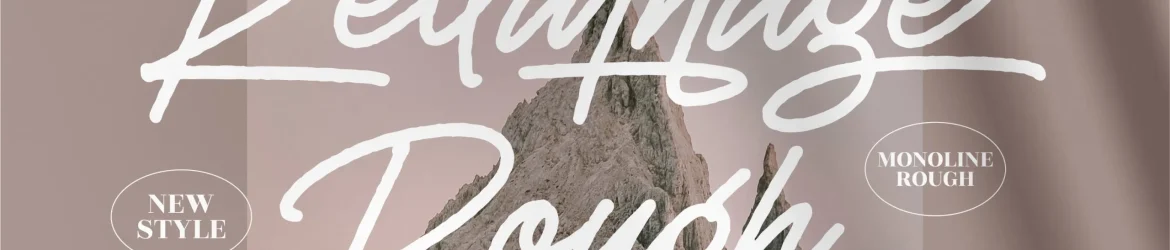
Rellathage Rough Font – Fonte Grátis
Rellathage Rough Font
A fonte “Rellathage Rough” é uma escolha ideal para projetos que exigem um toque autêntico e sofisticado. Com seu estilo handwritten, esta fonte traz um toque natural a qualquer projeto que você possa imaginar – seja um logomarca, cartão de nome, convite ou até mesmo etiquetas de embalagem. Seja para personalizar sua casa com itens de decoração única, fazer camisetas personalizadas, criar capas de livros ou mugs únicos, a “Rellathage Rough” está aqui para dar um toque especial ao seu design. Além disso, esta fonte é perfeita para projetos que exigem uma sensação de exclusividade e premium. Seja para embalagens de produtos de luxo ou até mesmo a própria capa do seu próximo livro best-seller, você pode garantir um design único e memorável com esse recurso gráfico. Com sua elegância natural e detalhes elaborados, a “Rellathage Rough” é uma escolha inteligente para qualquer designer que busca trazer sofisticação e autenticidade aos seus projetos. Seja qual seja o seu próximo projeto de design, certifique-se de usar essa fonte, você não vai se arrepender!